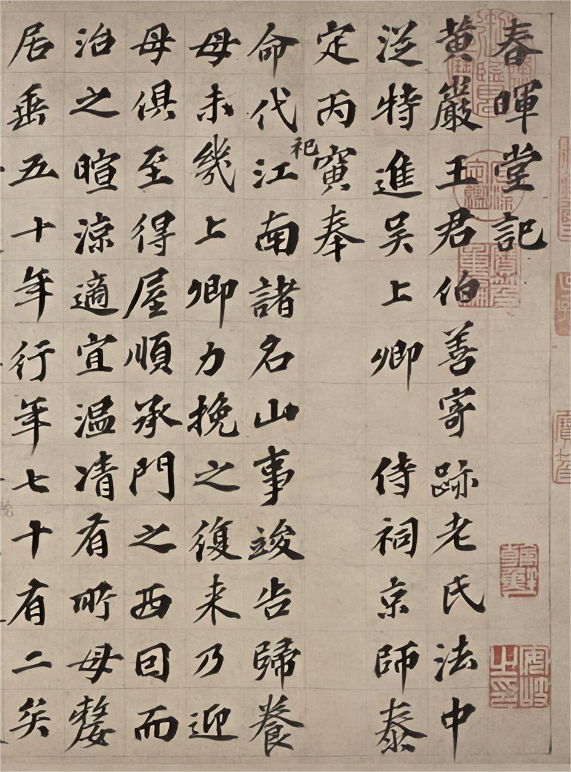
字体全名: 汉标欧阳玄楷书春晖堂记
字体简介: 下载须知:本字库非标准GB2312字库。本字库只包含了欧阳玄《春晖堂记》真迹上的“477个字”。春晖堂记卷,元,欧阳玄书,纸本,楷书,纵29厘米,横102.9厘米。署款:“国史冀郡欧阳玄记”,款下钤“冀郡欧阳玄印”。鉴藏印有清安岐、乾隆内府、嘉庆内府、宣统内府诸印。